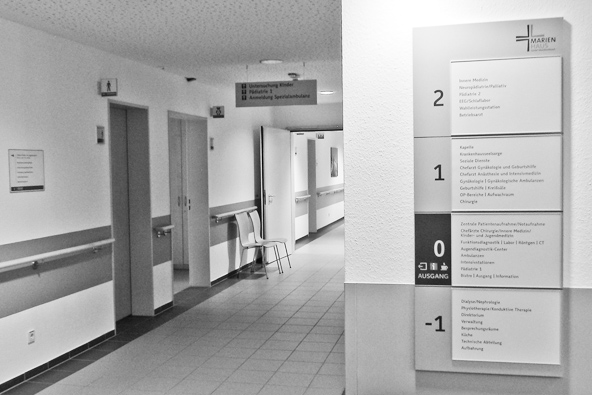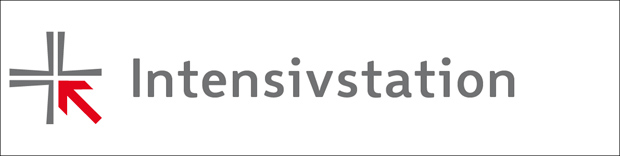
Typografie.info-Mitglied Burkhard Liermann von Protondesign in Völklingen hat das neue Leitsystem für die Marienhausklinik Kohlhof im Saarland entwickelt. Über Typografie.info fand er die passende Schrift für sein Projekt. Wir führten dazu ein Interview mit dem Designer.
Du bist ja schon seit Jahren im Bereich Werbung tätig. Gehört eigentlich der Bereich Beschilderung und Leuchtwerbung automatisch dazu?
Moderne Werbekonzepte müssen natürlich alle Bereiche berücksichtigen, und es zeichnet einen guten Designer aus, wenn er vielseitig ist. Deshalb gehören Schilder und Beschilderungen dazu und damit auch die Leuchtwerbung. Geschäftskunden legen heutzutage großen Wert darauf, dass sie alles aus einer Hand bekommen können. Die klassische Werbung mit Logo, Homepage, Flyern und Briefpapier ist noch immer wichtig, aber immer öfter habe ich in den letzten Jahren gehört: »Ich brauche da noch eine Schaufensterbeschriftung ...« Wenn ich ein Werbekonzept für ein Restaurant erstelle, dann gehört neben der Speisekarte eben auch die Leuchtwerbung dazu, vielleicht zusätzlich ein beschrifteter Pylon im Eingangsbereich. Für mich ist es jedenfalls eine selbstverständliche Serviceleistung, dass ich meine Kunden auch im Hinblick auf die Gestaltung von Leuchtwerbung und Beschilderung kompetent und effektiv beraten kann.
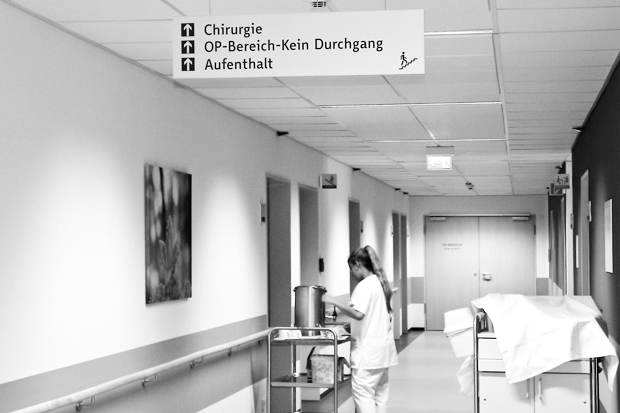
Inzwischen kann ich mit meinen Partnern auch Sonderlösungen – wie mit zwei Radien gebogene Schriftzüge, gebogene Fronten mit dekupiert und durchgesteckten Acrylglasbuchstaben sowie tief- oder hochgezogene Logos etc. realisieren. Durch den Fortschritt der LED-Technik, durch die Vielfalt der zur Verfügung stehenden Maschinen und Elektronik ist in diesem Bereich nahezu alles möglich – auch computergesteuerte Leit- und Orientierungssysteme.
Wie kam es zum Auftrag für die Gestaltung der Marienhausklinik Kohlhof und in welchem zeitlichen Rahmen wird so ein Projekt bearbeitet?
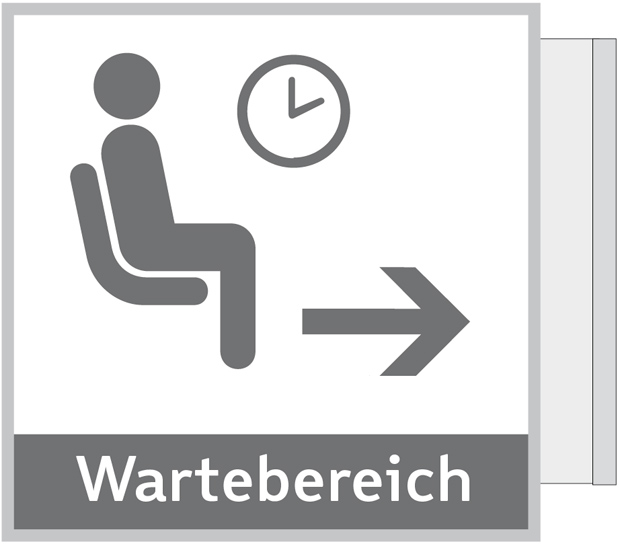
Der Auftrag wurde mit Fördergeldern realisiert, und die öffentliche Ausschreibung war auf bekannten Ausschreibungsportalen hinterlegt. Ein Anruf beim Architekten, der als Ansprechpartner genannt war, brachte mir einen ersten Kontakt und zusätzlich viele Hinweise zu meinen Fragen. Solche Kontakte zu Entscheidern, Auftraggebern und Generalunternehmern sind -auch schon im Vorfeld-immens wichtig.
Im Normalfall sollte man vier bis sechs Monate für die Vorbereitung einplanen. Je nach Anzahl der Entscheider, Gremien, Arbeitsgruppen etc. kann sich so ein Projekt schon im Vorfeld ziemlich hinziehen. Es sind viele Absprachen und Entscheidungen mit vielen unterschiedlichen Beteiligten nötig. Bei solchen Runder-Tisch-Gesprächen sollte man die Meilensteine der Projektphasen genau im Kopf (oder auf Papier) haben, um so viel Fragen wie möglich zu klären.
Mit welchen Parteien arbeitet ein Designer bei so einem Projekt zusammen?
In der Regel gibt es direkte und indirekte Ansprechpartner. Je nach Auftrag sind hier zu nennen: der Generalunternehmer, der Architekt, der Projektsteuerer, der Endkunde mit seinen diversen internen Gremien oder Arbeitsgruppen (Direktorium, Chefärzte, Ärzte, Personal, technische Leitung etc). Wichtig ist es, von Anfang an einen einzigen Hauptansprechpartner und Entscheider zu finden, den man dann in allen Belangen konsultieren kann.
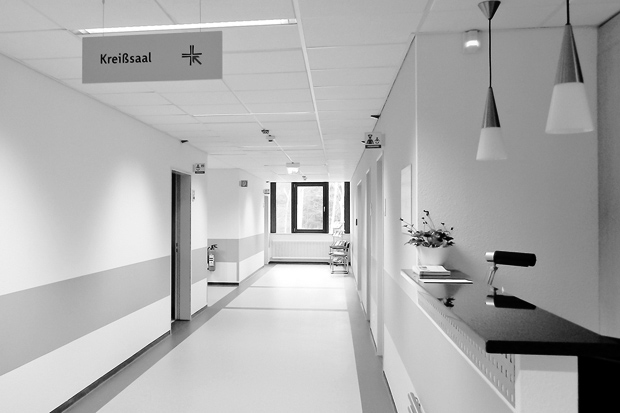
Wo liegen typische Probleme und Stolperfallen?
Als ich angefangen habe, in diesem Bereich tätig zu werden, war es besonders problematisch für mich, wenn sich ein Projekt verselbstständigt hat und untergeordnete Gruppen bei wichtigen Entscheidungen mitreden wollten. Damals habe ich gelernt: Um das Projekt im Auftragsrahmen zu halten, müssen konsequent die vereinbarten Regeln eingehalten werden. Sonst kann das ganze Projekt gefährdet sein. Das gezielte und sorgfältige Projektmanagement vor Beginn der Bauphase hat also oberste Priorität. Fehler wie falsche Maße, Schätzungen und nicht sorgfältig ausgeführte Aufmaße, können in der Ausführungsphase zu Problemen führen, die dann nebenbei auch noch gelöst werden müssen. In der Hochphase gilt es, zu kontrollieren, abzugleichen, Monteure zu unterrichten, zu motivieren und immer den Überblick zu behalten. Des Weiteren müssen jederzeit die Budgetkontrolle, Arbeitsstundenkalkulationen etc. im Blickfeld bleiben.
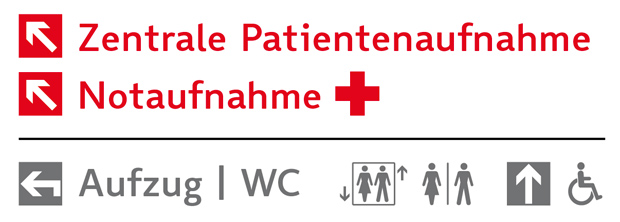
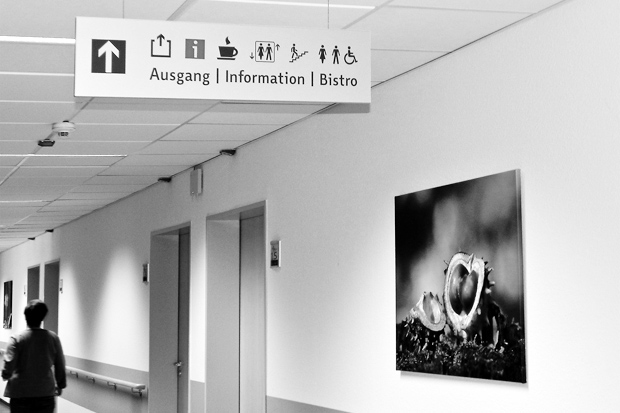
Was ist das Besondere an der Beschilderung von Krankenhäusern?
Im Gegensatz zu offen gestalteten Räumen wie Bahnhöfe sind Krankenhäuser berühmt für ihre langen, möglicherweise noch verschachtelten Gänge, in denen man schnell die Orientierung verliert. Hinzu kommt, dass die Besucher und das Personal unterschiedliche Ziele haben können. Also heißt die Herausforderung: Wie findet man die typischen Laufwege der Benutzer? Und wie gestaltet man die Beschilderung an den Entscheidungspunkten so, dass sie für alle Benutzer funktioniert?
Grundsätzlich gilt: Ein Leitsystem muss durch Konsequenz überzeugen, durch eine klare Struktur und einheitliche grafische Merkmale, die Hinweisgeber (Schilder und Zeichen) müssen eine einheitliche Zeichensprache und Formgebung haben. In der Marienhausklinik haben wir uns für eine Gliederung entschieden, die wir in eine »vertikale Linie« (4 Etagen) und eine »horizontale Linie« (innerhalb der Etagen bzw. Fachabteilungen) eingeteilt haben.
Die vertikale Linie umfasst zunächst Etagenwegweiser in den Fahrstühlen selbst und gegenüber den Fahrstühlen in den Etagen. Gegenüber den Treppenhausausgängen befinden sich jeweils DIN A3-Schilder mit einer Kurzbeschreibung der nächsten Ziele rechts und links.
In der horizontalen Linie wurden zunächst Deckenwegweiser verteilt. Sie dienen der groben Richtungsweisung in die Fachabteilungen (z. B. Neuropädiatrie, Geburtshilfe etc). Zusätzlich wurden die Türen mit Klartext (ausgeschriebenen Abteilungsnamen) gekennzeichnet.
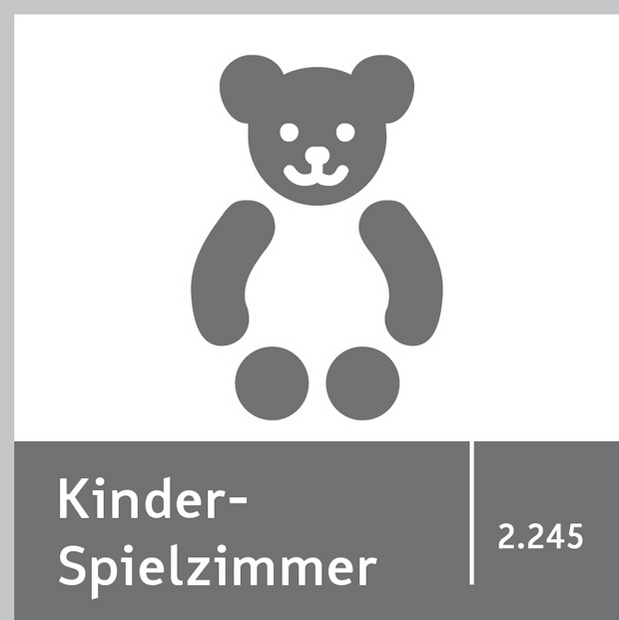
Wenn es nur nach dem Architekten gegangen wäre, hätten einige Schilder nicht montiert werden dürfen. Ich bin aber der Ansicht: Ein gutes System integriert sich in die Architektur, unterstreicht die Eleganz und Klarheit der Raum- und Flurplanung. Die Beschilderung sollte unauffällig, aber wirksam sein. Bei der Positionierung der vielen verschiedenen Schilder waren Ausnahmen die Regel und Sonderlösungen an der Tagesordnung. Da hängt am idealen Standort für ein Schild ein Feuerlöscher an der Wand oder ein Bild beansprucht den besten Platz für die Wegeführung. Dort, wo gebohrt werden muss, liegt ein Kabel unter Putz, oder ein Feuermelder blockiert den längst festgelegten Wandbereich. Trotz genauester Vorplanung kann man nie alle Unwägbarkeiten berücksichtigen. Und einen guten Projektmanager erkennt man auch daran, dass er mit diesen Herausforderungen flexibel umgehen kann.